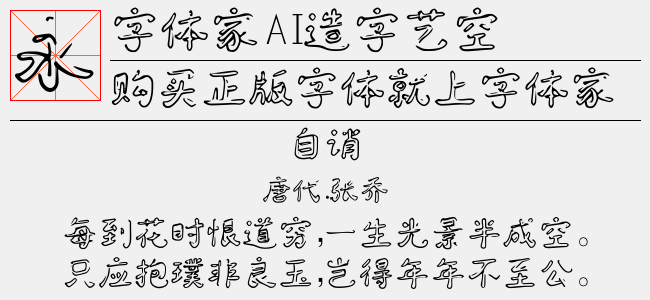
字体家AI造字艺空
字体名称: 字体家AI造字艺空
字体风格: 空心
字体家AI造字艺空是一款由字体家AI神笔造字生成的一款艺术字体,笔画为空心花体设计,字形灵动活泼,通过设计师与AI造字的智能配合,使这款字体整体统一,书写的很有趣味感。比较适合用于平面设计等。
字体家AI造字艺空”是一款书写很新颖的字体,字体大方,适合各种设计作品使用!欢迎下载!